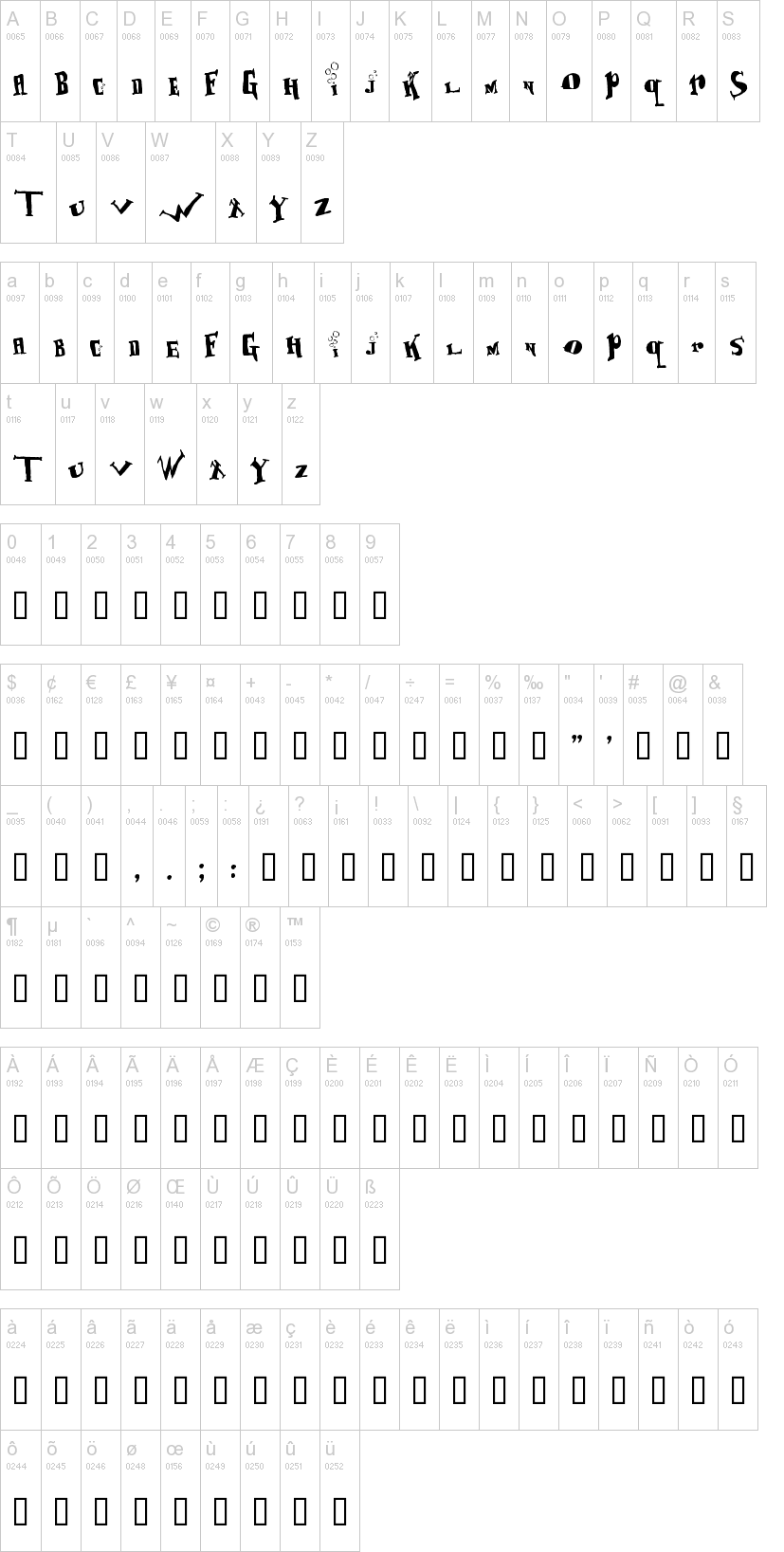
BabOonjaZzbaSsOon
BabOonjaZzbaSsOon 是一款自由的手写字体,它具有明亮而活泼的特点,可以满足不同的设计需求。字体的设计灵感来自西班牙语中的“Baboon”,它的字母看起来有点像一只可爱的猴子,因此它的名字也可以翻译为“猴子字体”。BabOonjaZzbaSsOon 字体具有自由、独特和快乐的特点,可以用于各种类型的设计,如招牌、海报、卡片、T恤等。
BabOonjaZzbaSsOon是一款非常不错的手写艺术字体,具有很好的视觉感,适合于文化类的宣传设计、商业类品牌的广告和产品包装设计以及个性化文字排版等较多场景。
BabOonjaZzbaSsOon字符映射图